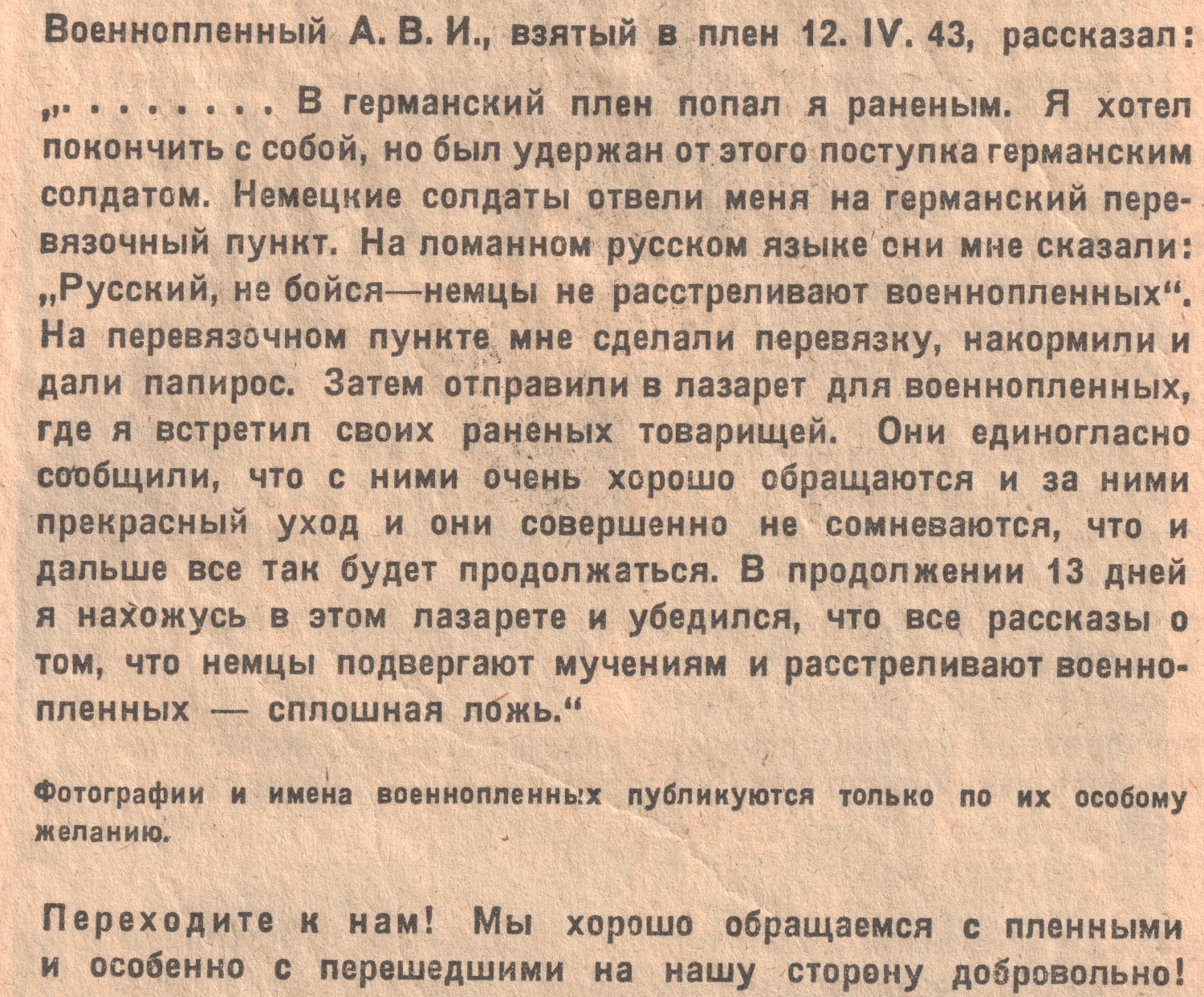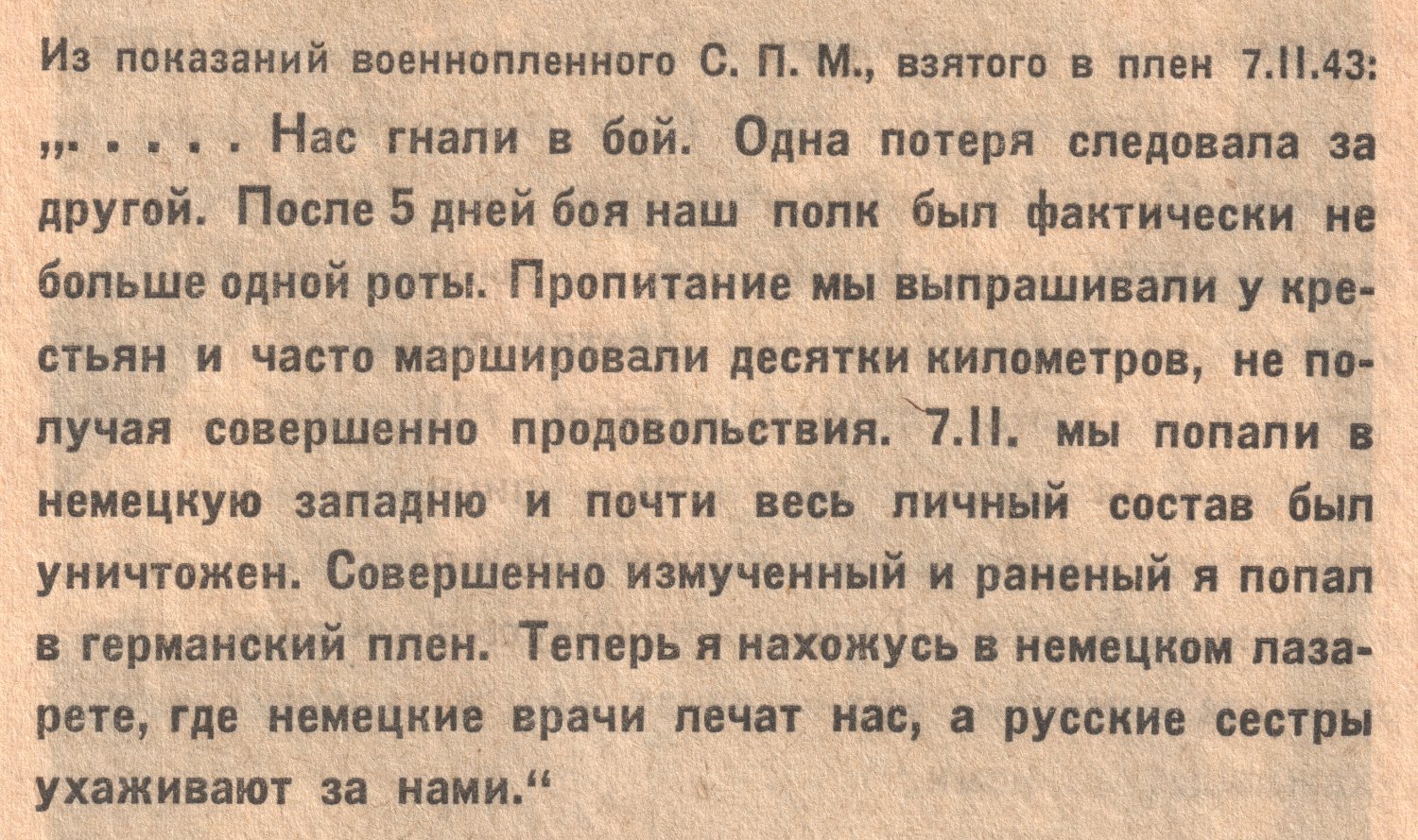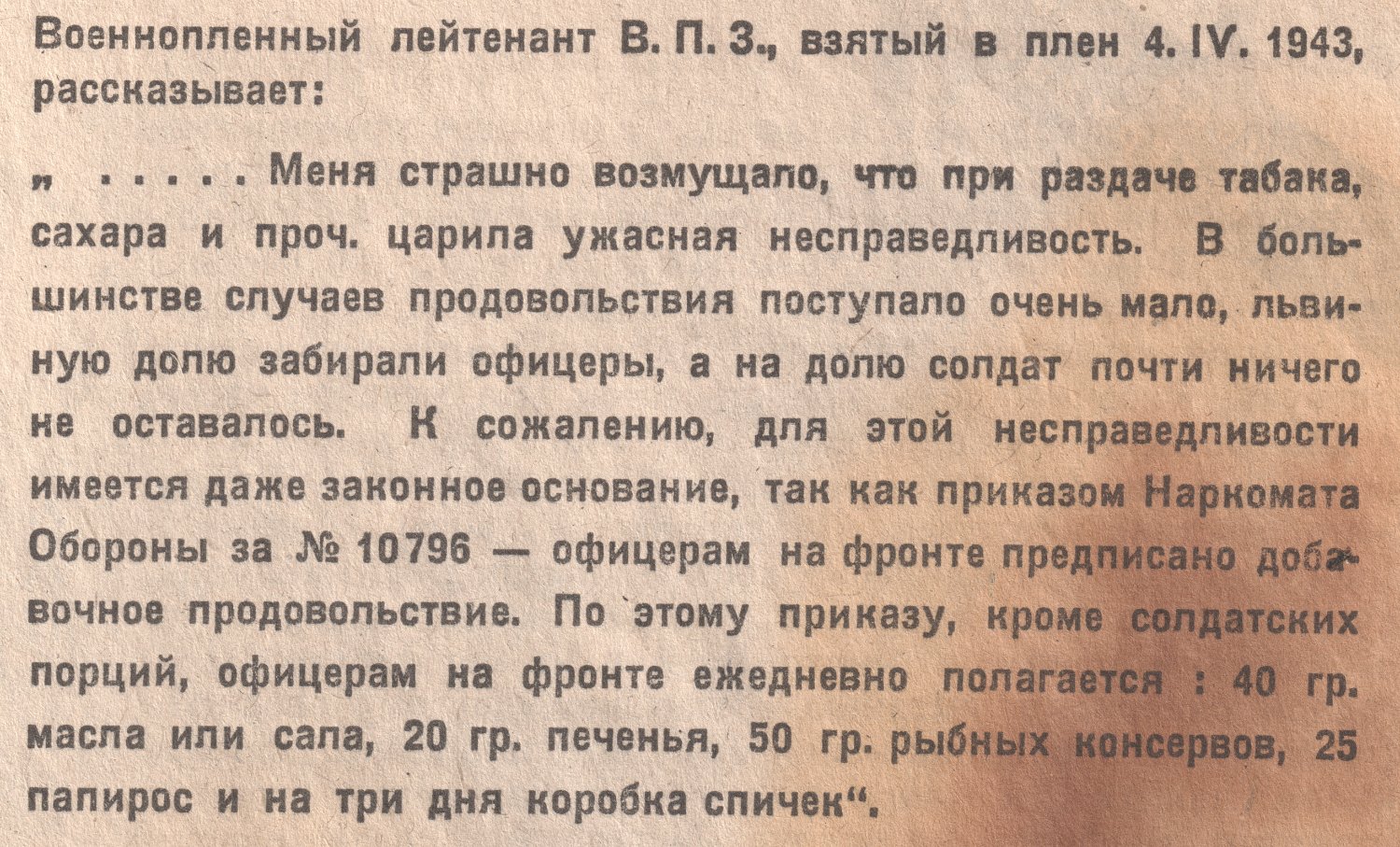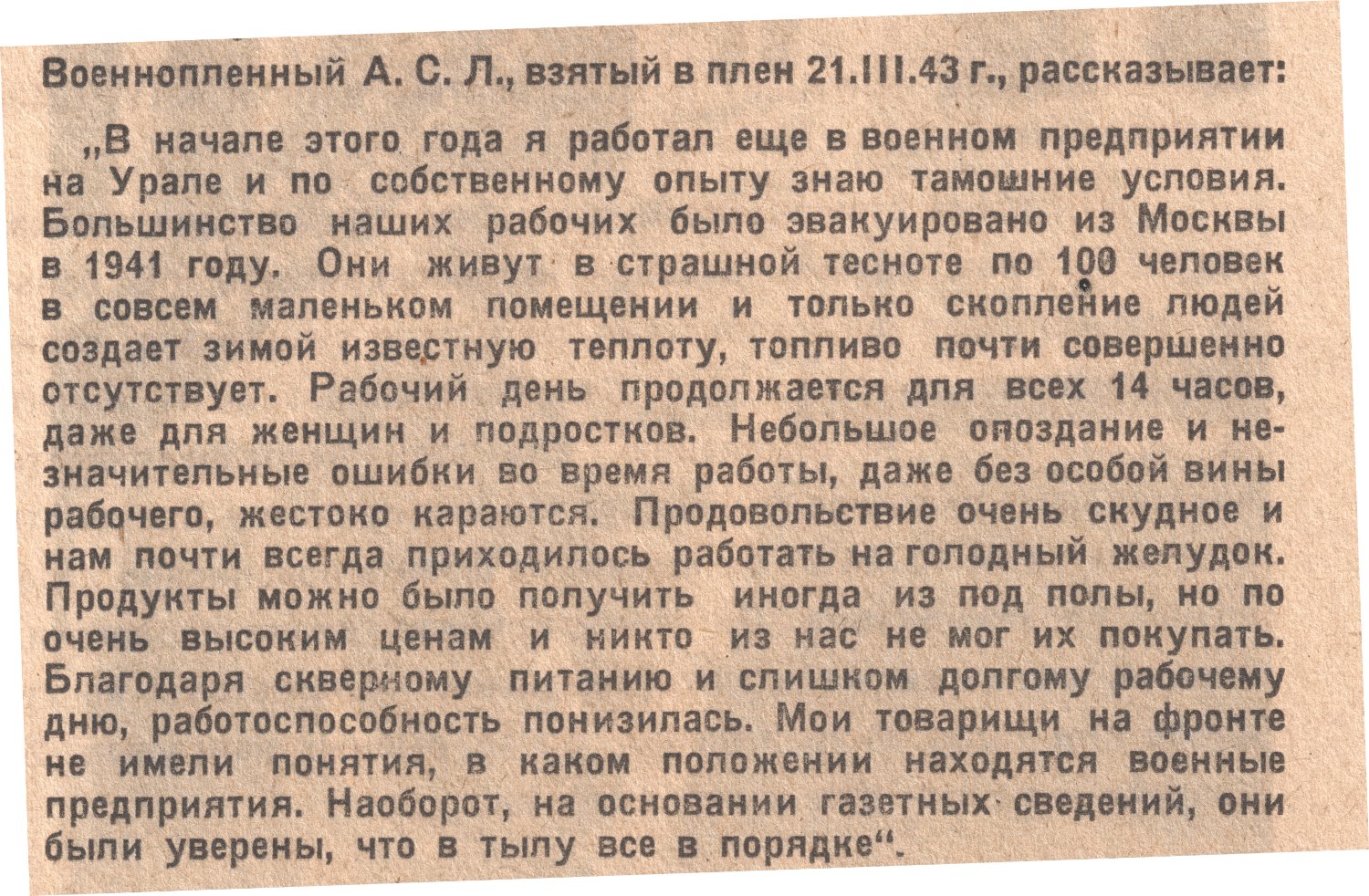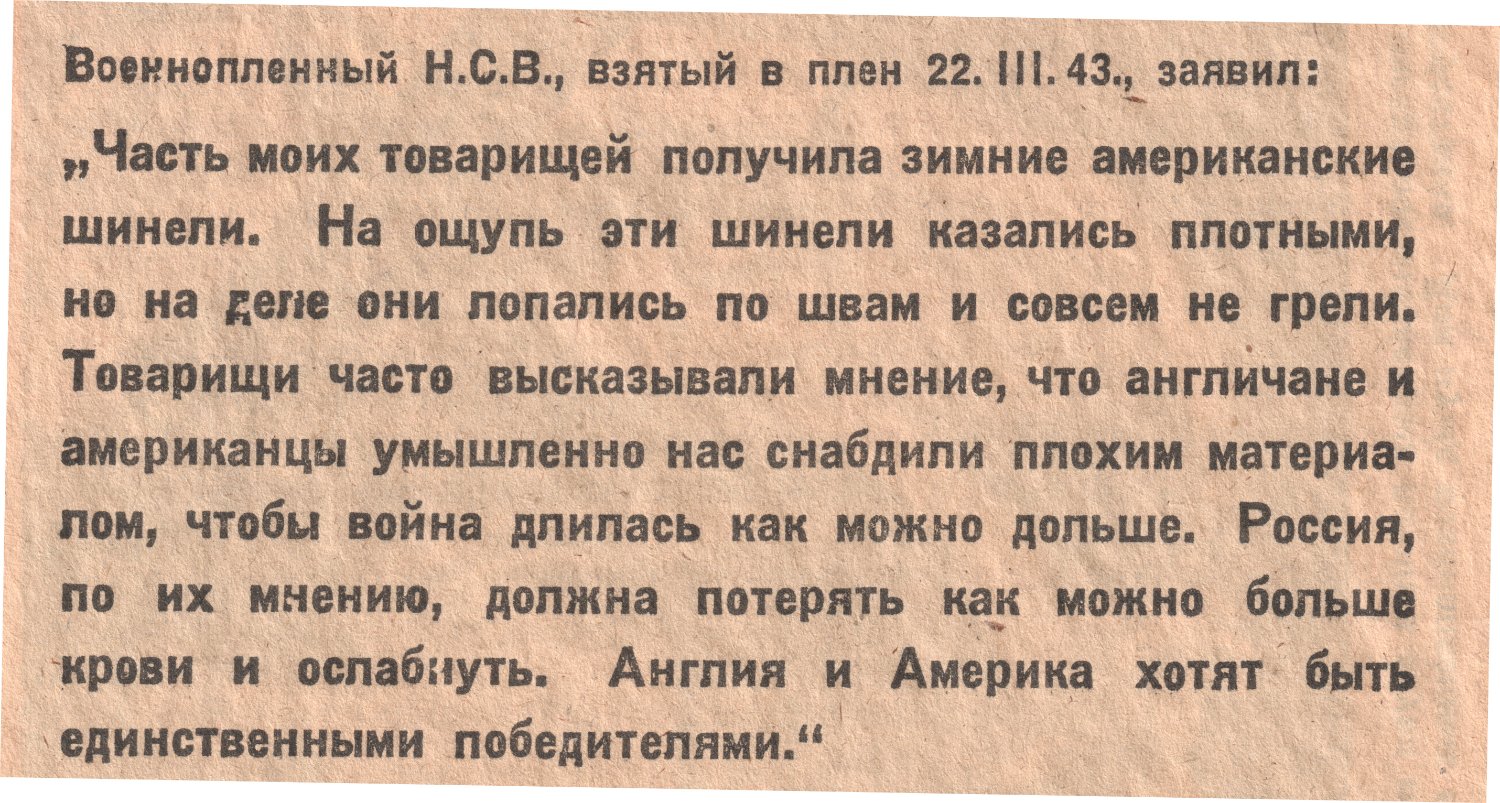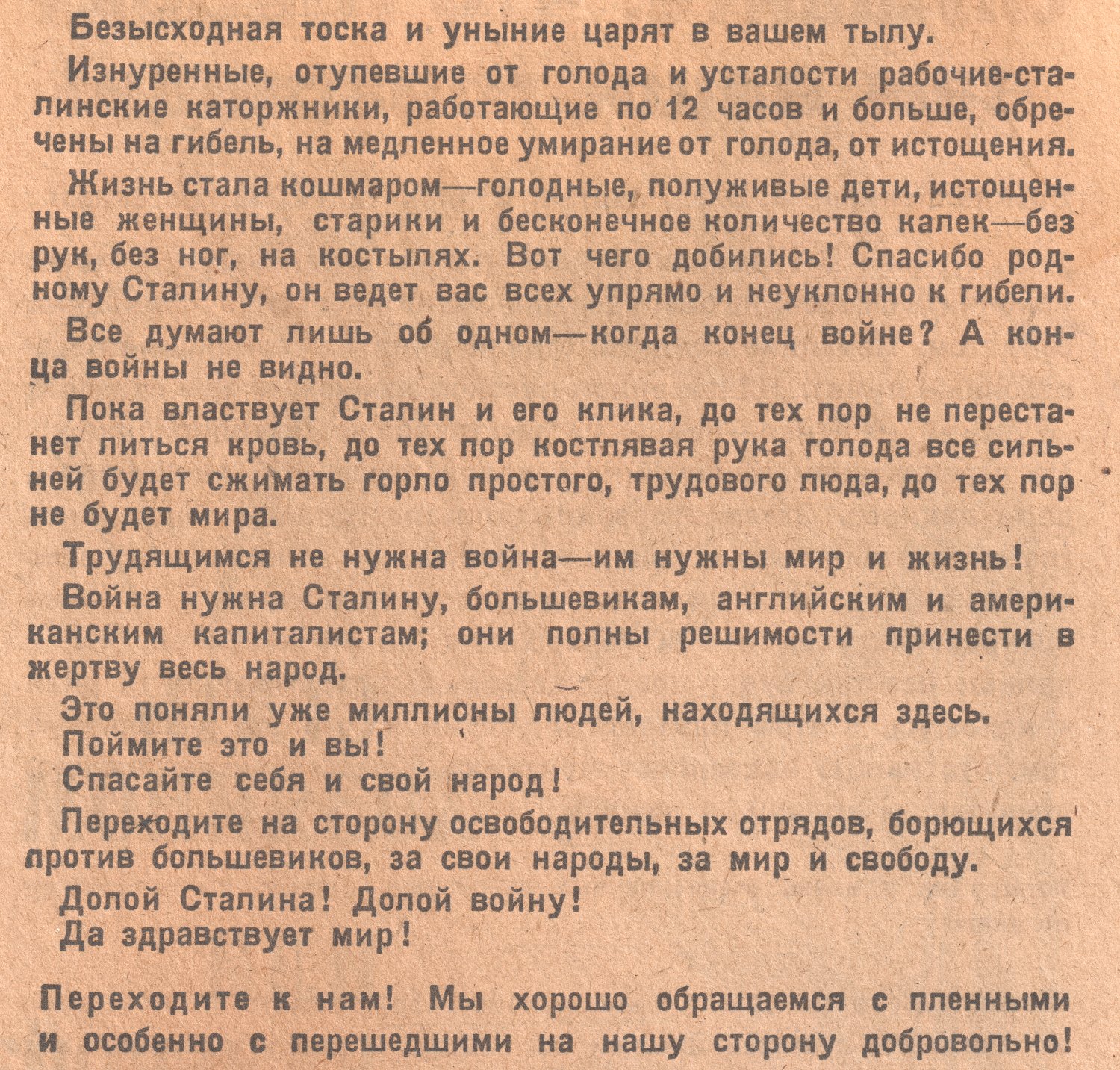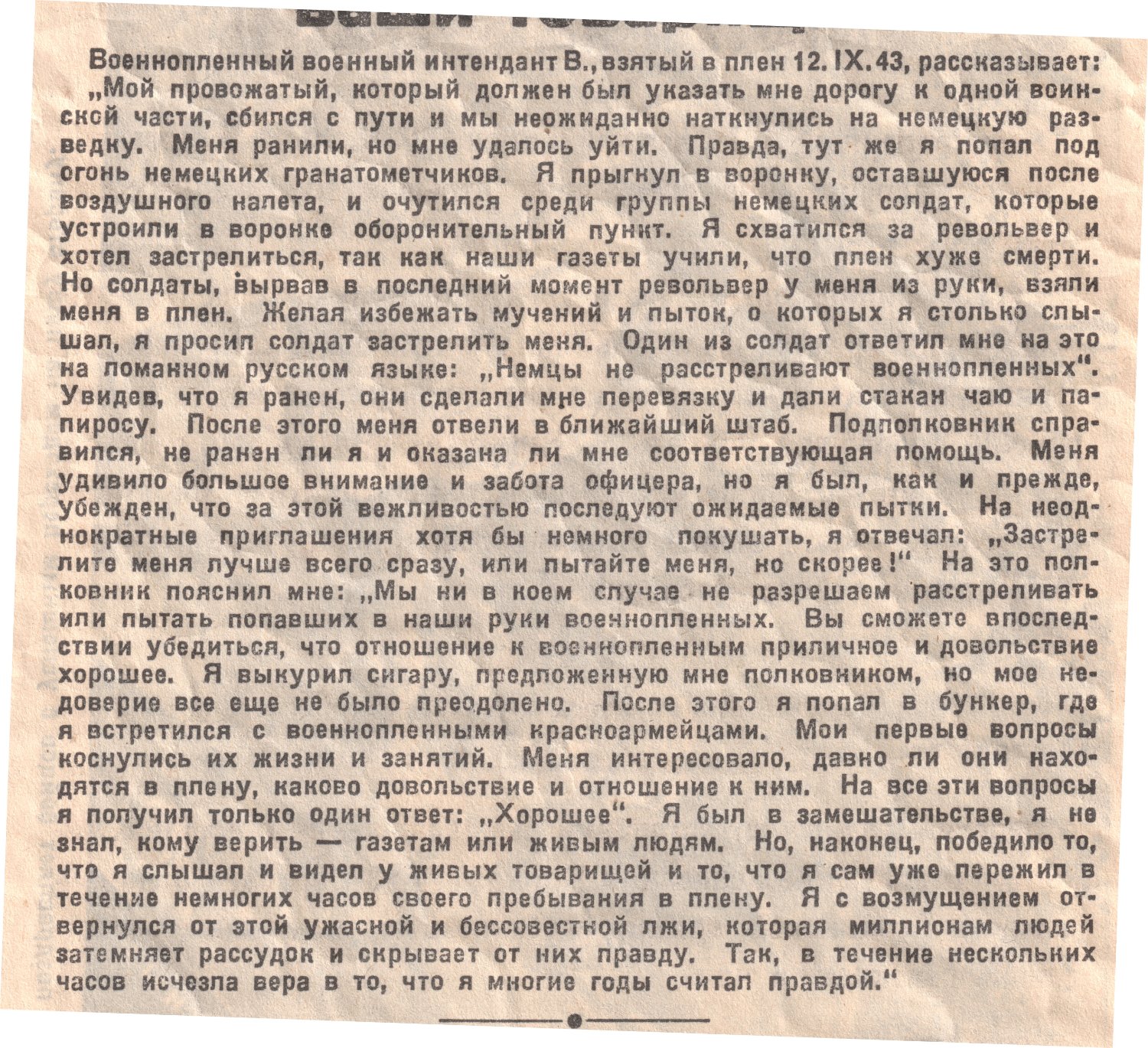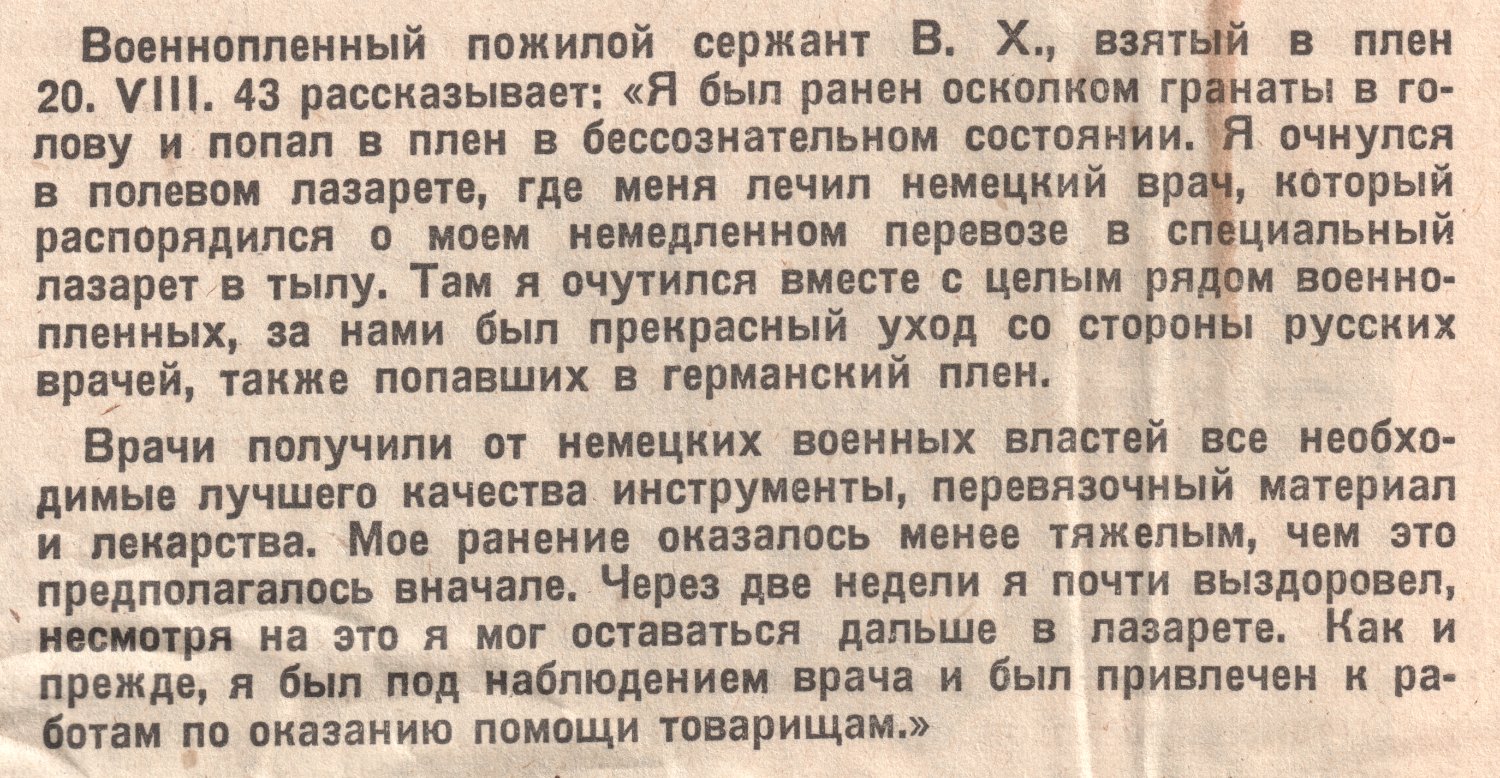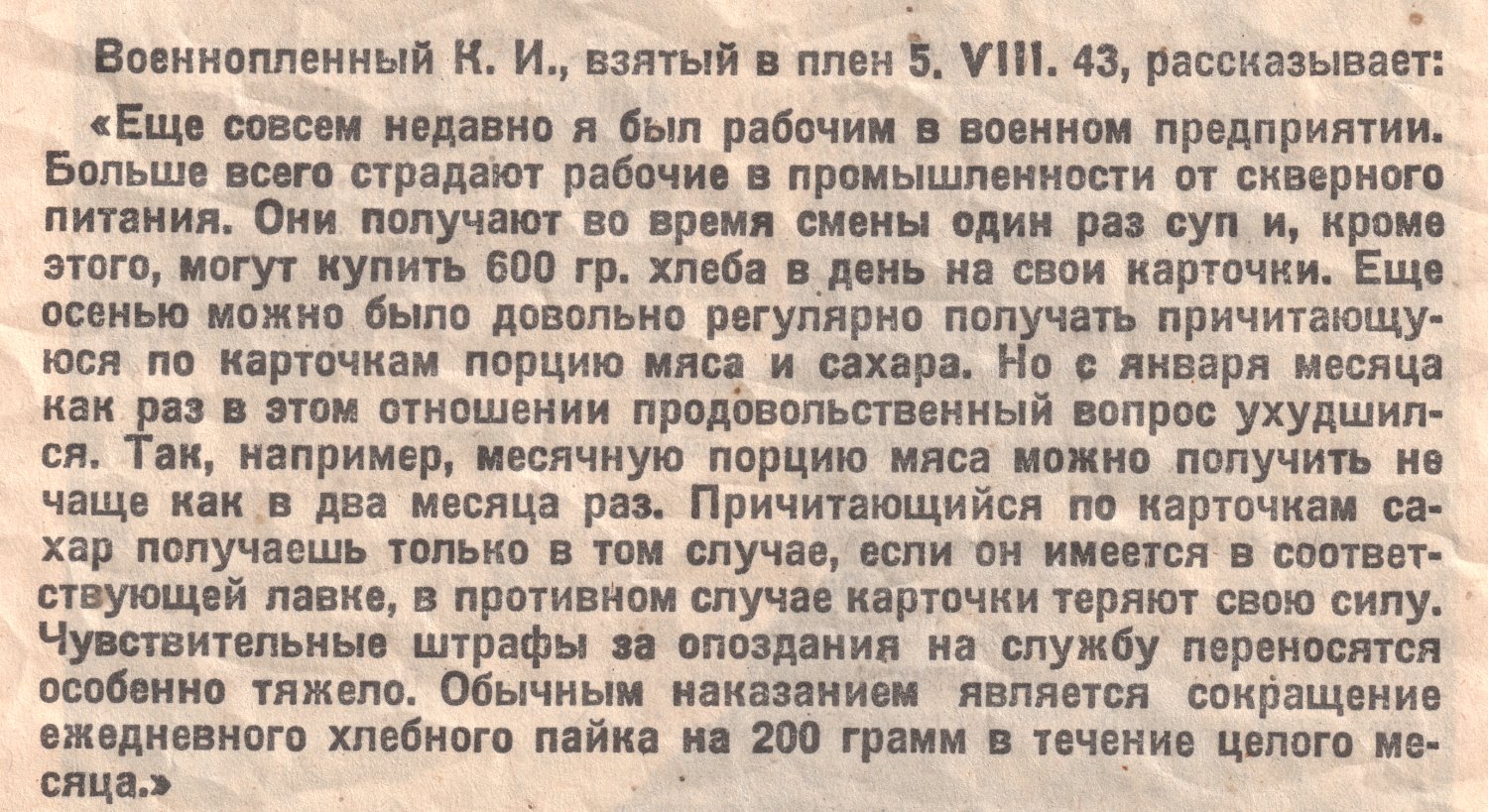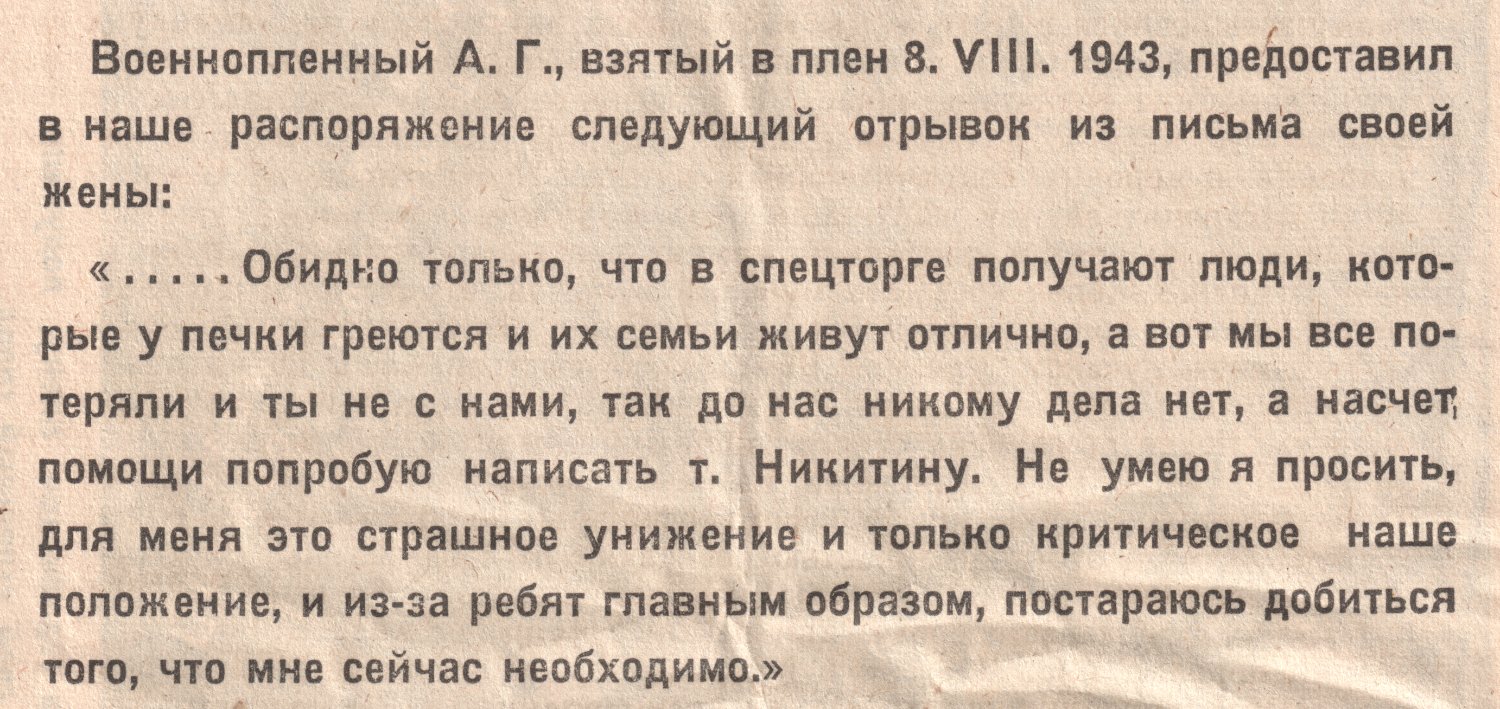
Шрифты в немецких и советских листовках 1941-1945
Массово гротеск пошел в ход с 1943 г. и применялся ими до конца войны. Гарнитуру на приведенном примере не смог идентифицировать (возможно, там даже разные шрифты для заголовка и основного набора).
Кириллицу не нашел, но Бертольд делал ее
А насчет шрифта Gill Sans (жирное начертание) применительно к слову PASSIERSCHEIN я, получается, ошибся?
Gill похож, наверное он, там R характерная
Массово гротеск пошел в ход с 1943 г. и применялся ими до конца войны. Гарнитуру на приведенном примере не смог идентифицировать (возможно, там даже разные шрифты для заголовка и основного набора).
Практически закончил статью, но не могу понять, что за гротеск использовался в основном наборе листовок (см. цитированное сообщение)... Перебрал кучу немецких гротесков, но везде нехарактерная "к", не могу понять... Вроде чем-то напоминает Monument (Genzsch&Heyse), но литера "к" выпадает...
Этот?
Вроде нет, тут квадратнее и полностью закрытый
В кириллице она обычно другой формы
Да, теперь вижу, что у "монумента" буква "а" другая... Сейчас в каталоге Бертольда гляну еще.
Этот?
Вроде нет, тут квадратнее и полностью закрытый
В кириллице она обычно другой формы
Еще довольно похожий шрифт - Полужирный книжный гротеск (Госполиграфтрест, 1927), но там нижний хвостик у "к" другой...
Я попробую из нескольких листовок собрать шрифт целиком, чтобы было нагляднее...
Этот?
Вроде нет, тут квадратнее и полностью закрытый
В кириллице она обычно другой формы
Попробовал собрать полный алфавит, отсканировав свои листовки в 1200 dpi. Вдруг это облегчит поиск, а то я потерялся в догадках...
Шрифт листовок ОКВ 1943 гротеск.jpg
По моему это несколько разных гротесков, разная ширина, толщина штрихов.
Akzidenz Grotesk вы же смотрели уже? Это из немецких листовок?
По моему это несколько разных гротесков, разная ширина, толщина штрихов.
Akzidenz Grotesk вы же смотрели уже? Это из немецких листовок?
Да, это из листовок. Если заглавные буквы собирал по разным образцам, то строчные почти все из одной листовки...
Привел примеры, откуда брал буквы. Возможно, я ошибаюсь, и это разные шрифты.
Попробуйте найти несколько П и Х. Может быть это сборная солянка из рассыпанной кассы?
Приложил фрагменты-исходники выше. Вроде бы П и Х похожие везде. Насчет рассыпанной кассы я не думаю, эти листовки печатал Берлин, крупные типографии по заказу верховного командования, там самодеятельность вряд ли допускалась...
Ничего не рассыпано, это разные шрифты, разные кассы, разного кегля в разных типографиях
а, даже так? Вот что значит, что я дилетант в Вашей сфере... мне они показались одинаковыми))
Я просто сравнил начертания, хвостики, апертуры, вроде похоже все. Но какие-то шрифты явно уже, какие-то шире.
К предыдущему вопросу про Akzidenz Grotesk - вроде бы не он, на мой - опять же, любительский - взгляд...
Шрифты же были железные, и кегль подогнать по размеру нельзя было — какой есть, такой и ставили. Хотя шрифт в листовках довольно оригинальный, буква "л" везде с широкой верхней площадкой. И "к" и "ж" с гнутыми ножками. Таких шрифтов, или, скорее их "потомков" не очень много. Asket, например, или Journal Sans.
И "к" и "ж" с гнутыми ножками
Это обычная форма для кириллицы и они там по разному гнутые
Таких шрифтов, или, скорее их "потомков" не очень много. Asket, например, или Journal Sans
ТС не нужны современные потомки. Журнальную уже нашли, но тут узкие закрытые гротески старого стиля.
У современных шрифтов есть предки, вот они может и поучаствовали в процессе. В сообщ. 29 шрифты похожие, возможно, что и не отечественные захваченные, а таки специально под листовки сделанные. В первом наборе более разнообразные были.
Почитай тему :)
Это обычная форма для кириллицы и они там по разному гнутые
ТС не нужны современные потомки. Журнальную уже нашли, но тут узкие закрытые гротески старого стиля.
Мне кажется, или шрифт напоминает вот этот?
Akzidenz-Grotesk Condensed in use
Я сразу посмотрел на "чистый" Akzidenz Grotesk, но узкое начертание у него отличается. Оно похоже по апертуре буквы "е", похожа литера "а", и нижние хвостики "R" похоже на то, что на наших литерах "К" и "Ж". Что скажете?